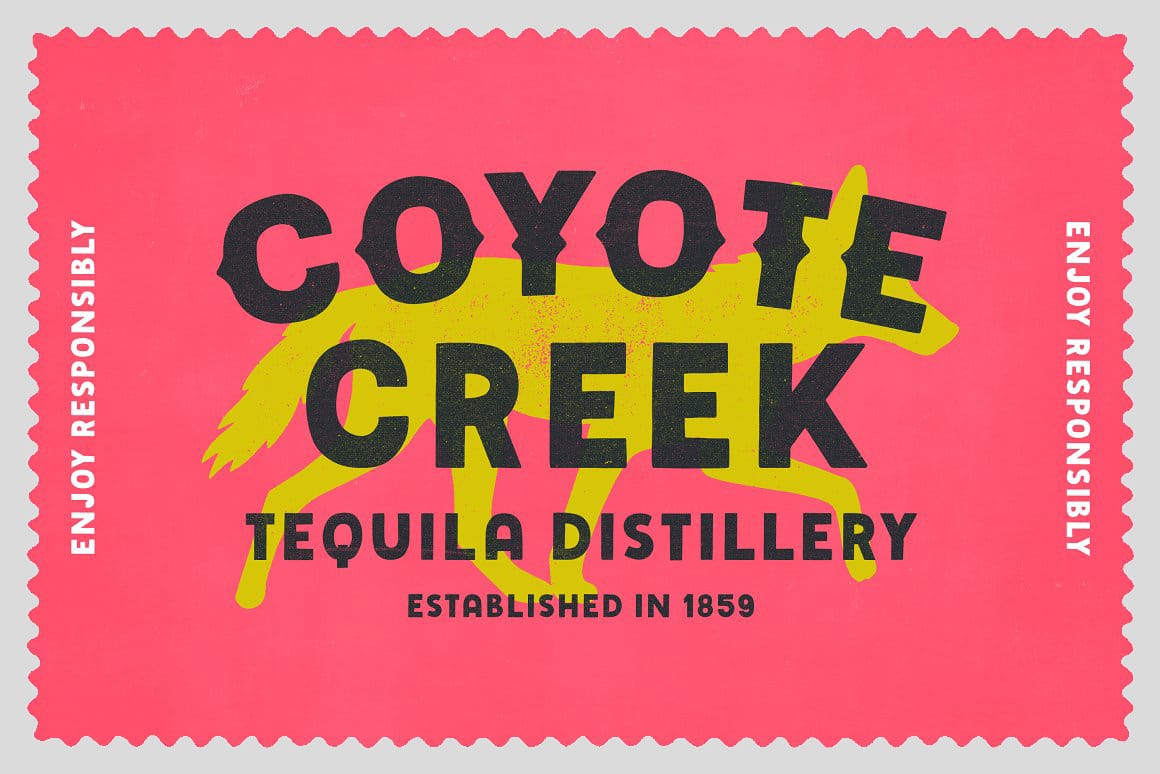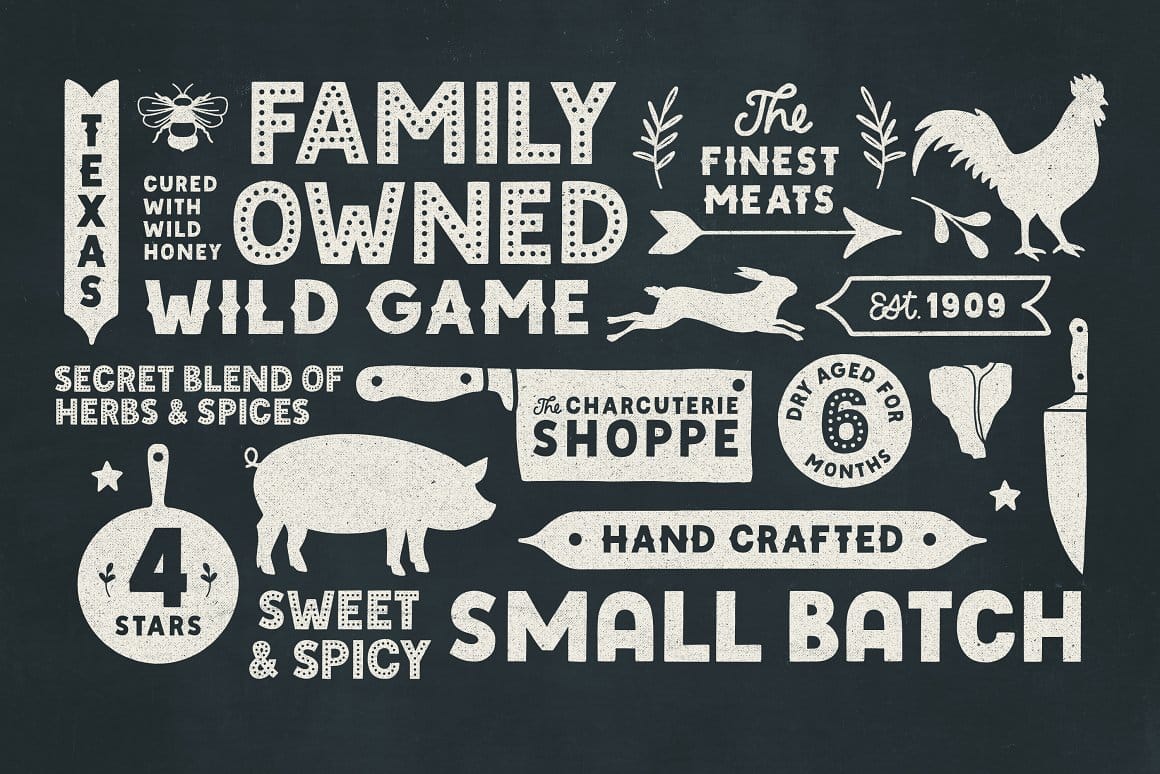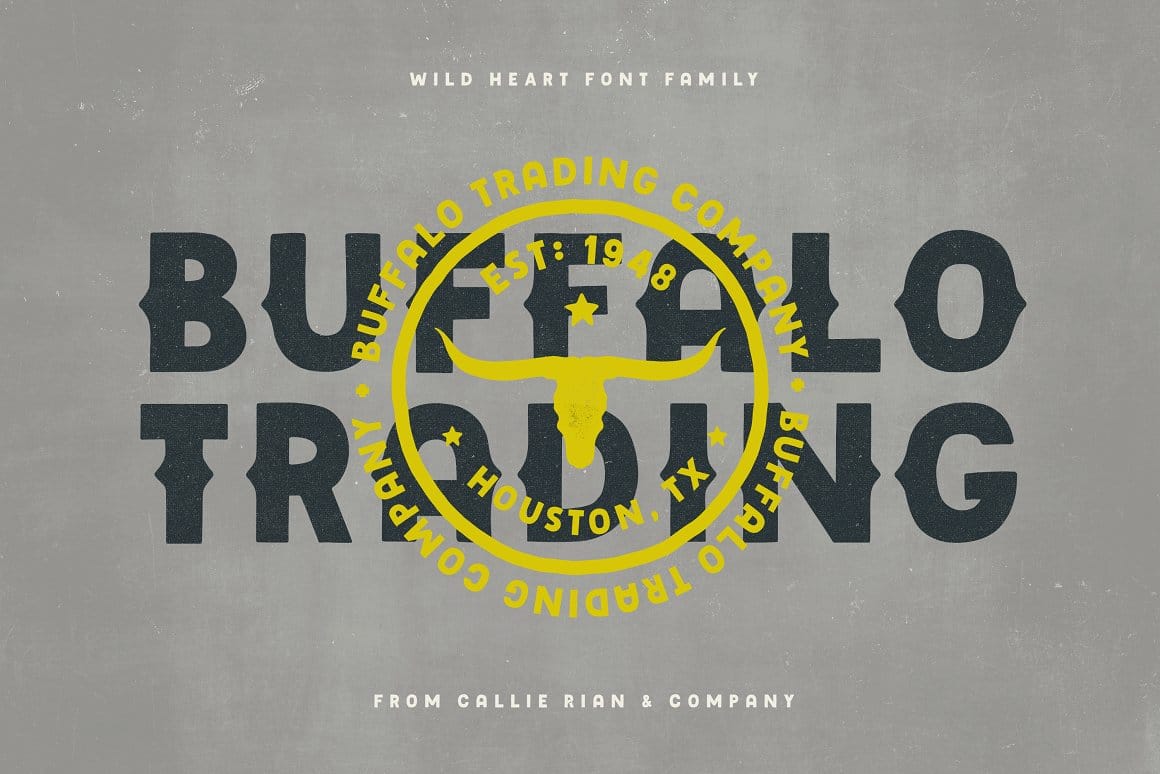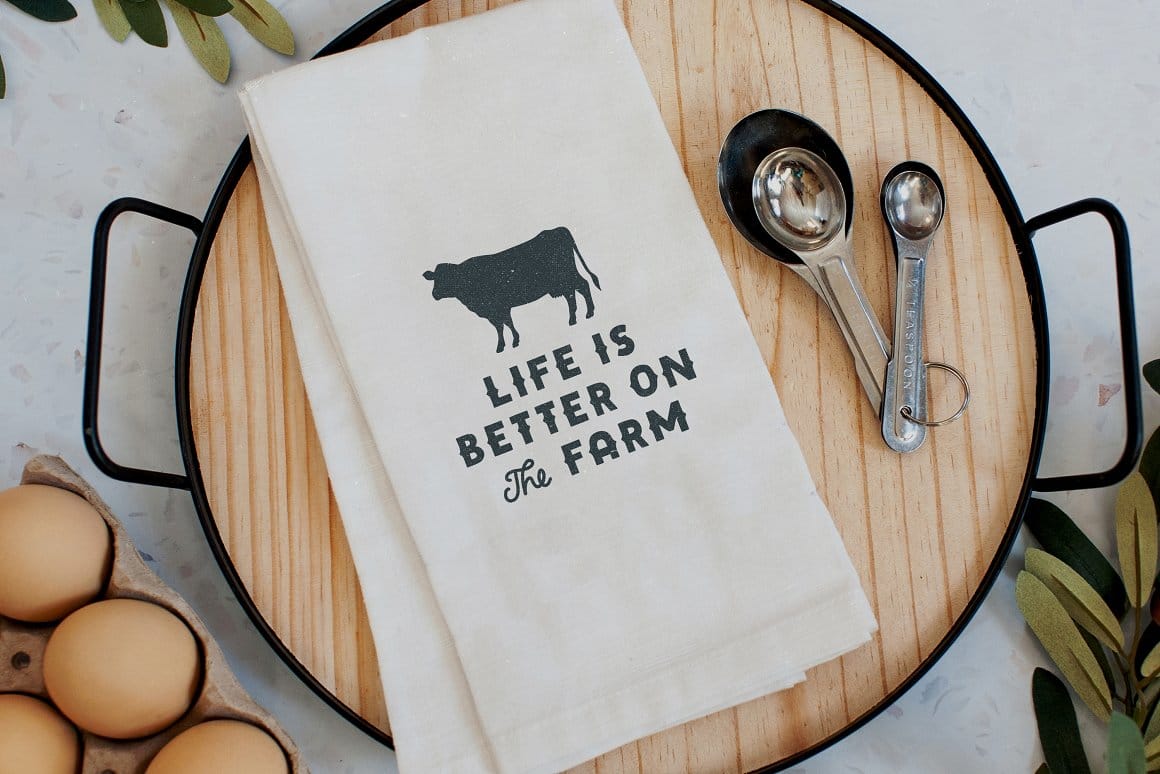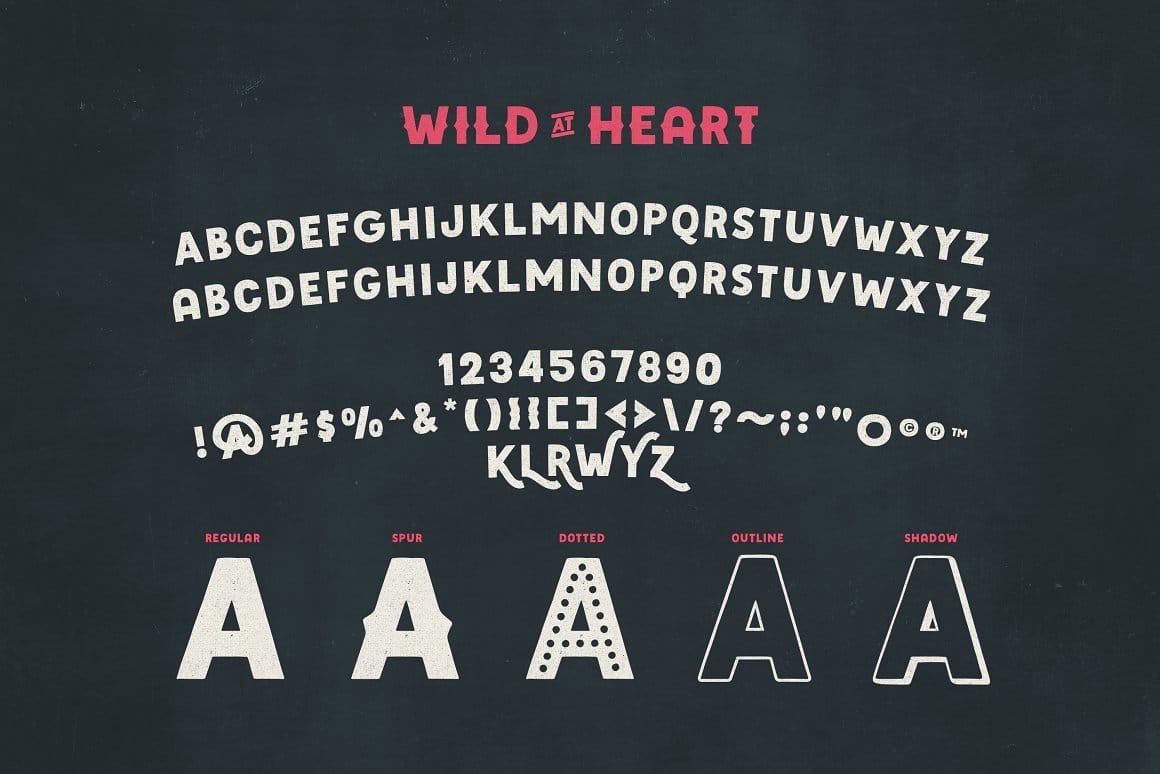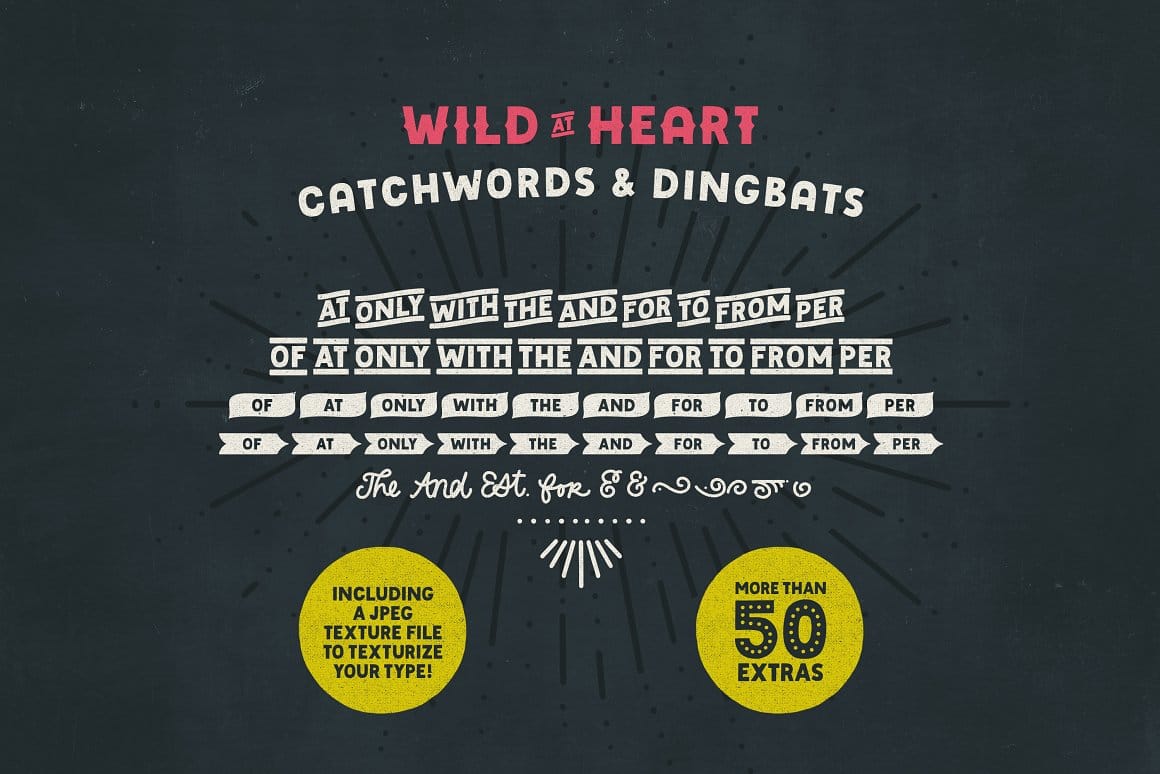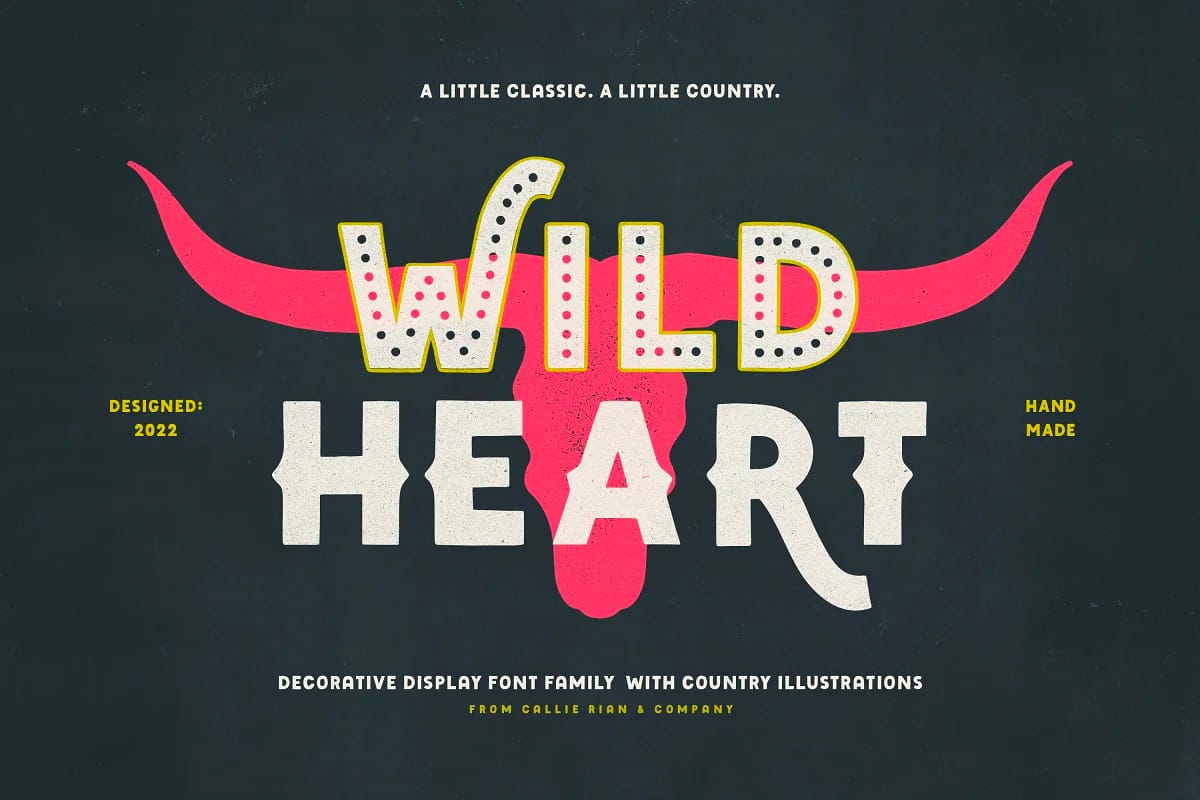
Wildheart Font Family là bộ phông chữ với 7 kiểu khác nhau mang hơi hướng một chút cổ điển lấy cảm hứng từ các thiết kế mạnh mẽ. Bạn có thể sử dụng bộ font này để tạo ra các thiết kế cổ điển với kiểu font có đường chấm hoặc đường viền hoặc có thể sử dụng phiên bản truyền thống với sự đơn giản của kiểu Wildheart Regular.